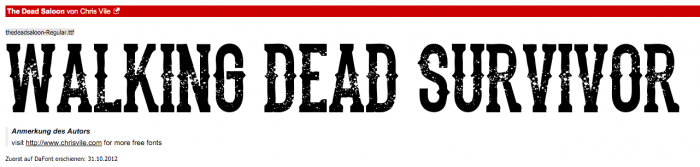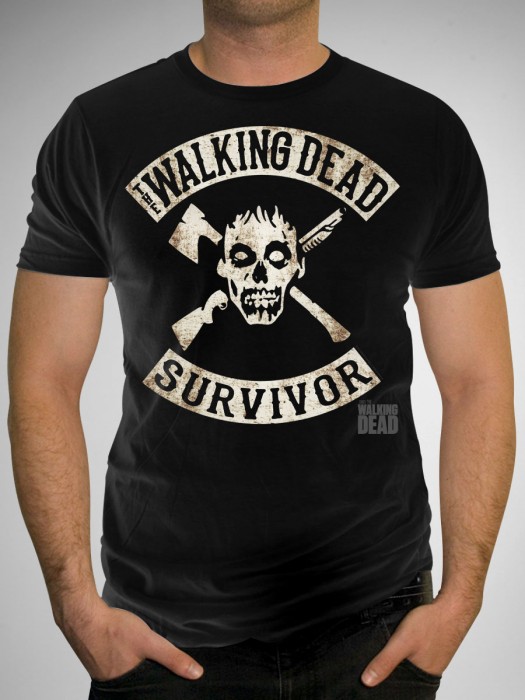
Suche Walking Dead Survivor Schrift
Ich kann leider nicht mit dem exakten Schriftnamen helfen, aber unter dem Stichwort »Wood« finden sich bei den verschiedenen Schrifthändlern eine Menge Fonts mit diesen Merkmalen.
Halbwegs nahe dran: